사인은 단순한 서명이 아니에요! 사인은 나만의 개성을 담아 표현하는 멋진 아이덴티티가 될 수 있죠. 유명인들의 사인만 봐도 각자의 개성이 한껏 담겨 있잖아요? ✨
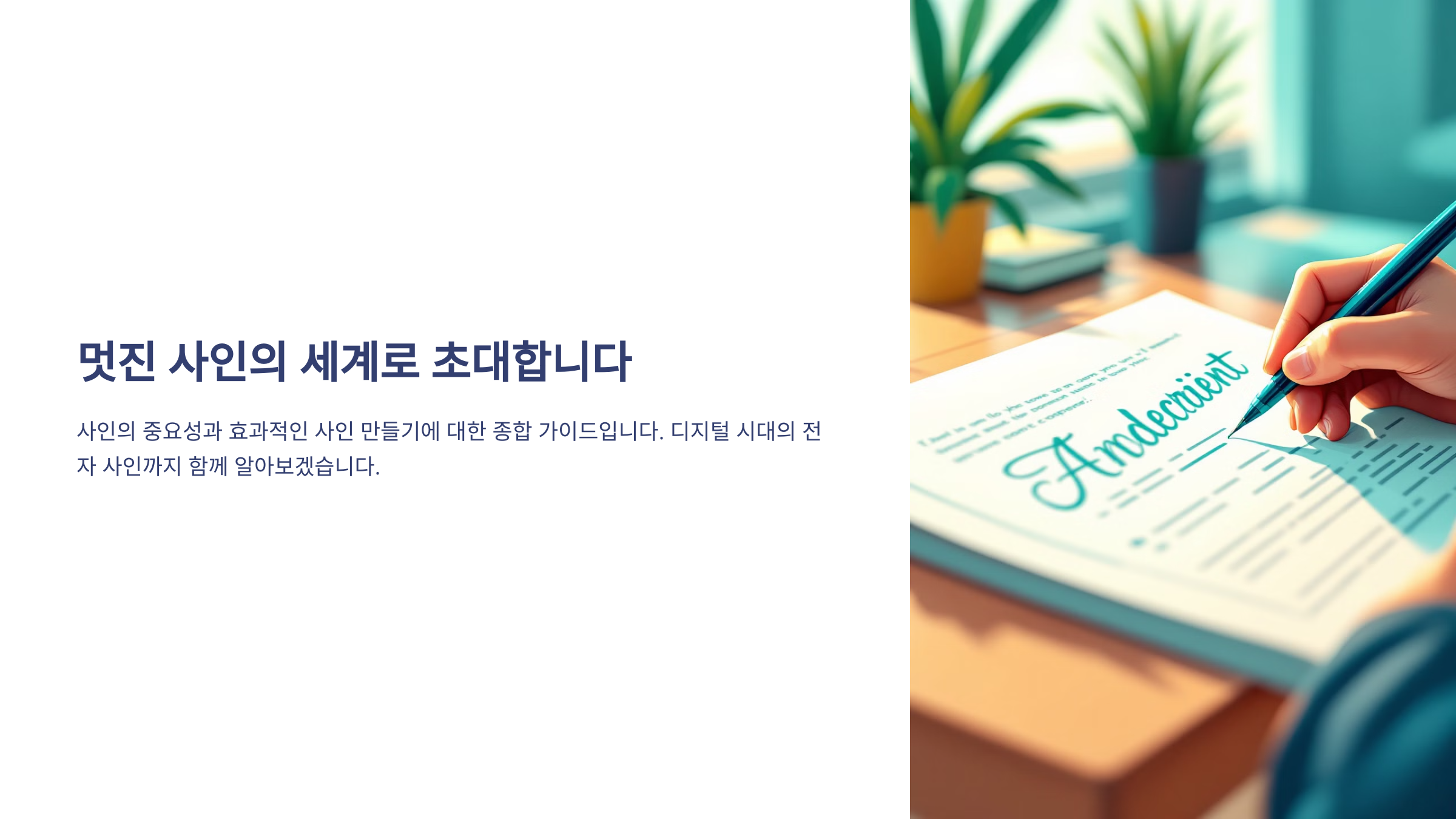
내가 생각했을 때, 멋진 사인은 단순하면서도 강렬한 인상을 주는 것이 중요해요. 한 글자만 바꿔도 느낌이 확 달라지기도 하고, 필기체를 응용하면 더욱 유니크한 디자인이 될 수도 있어요! 🎨
이제 본격적으로 멋진 사인을 만드는 방법에 대해 알아볼까요?
사인의 중요성 ✨
사인은 단순한 서명이 아니라, 자신을 표현하는 강력한 도구예요. 유명 연예인이나 스포츠 스타의 사인을 보면 한눈에 알아볼 수 있죠. 이것이 바로 사인이 가지는 브랜드 가치예요! 🌟
특히 예술가나 디자이너, 비즈니스맨에게 사인은 더욱 중요해요. 자신의 서명이 곧 하나의 트레이드마크가 되기도 하니까요. 예를 들어, 스티브 잡스나 일론 머스크 같은 유명 인물들은 사인 하나만으로도 강한 인상을 남기죠! 🚀
일상에서도 사인은 자주 쓰여요. 은행 서류, 계약서, 카드 서명까지, 우리가 사인을 하는 순간은 생각보다 많아요. 그렇다면 남들과 차별화된, 멋진 사인을 만들어야겠죠? ✍
📜 유명인의 개성 있는 사인 사례 🔍
유명인 사인의 특징 스티브 잡스 깔끔하면서도 독창적인 필기체 마이클 조던 강렬한 필체와 곡선 강조 일론 머스크 역동적이고 날렵한 스타일 방탄소년단(BTS) 각 멤버마다 개성 넘치는 디자인 이처럼 사인은 단순한 이름을 넘어서, 자신의 아이덴티티를 보여주는 중요한 요소예요. 그러면 어떻게 하면 나만의 멋진 사인을 만들 수 있을까요? 🎨
멋진 사인을 위한 기본 원칙 🎨
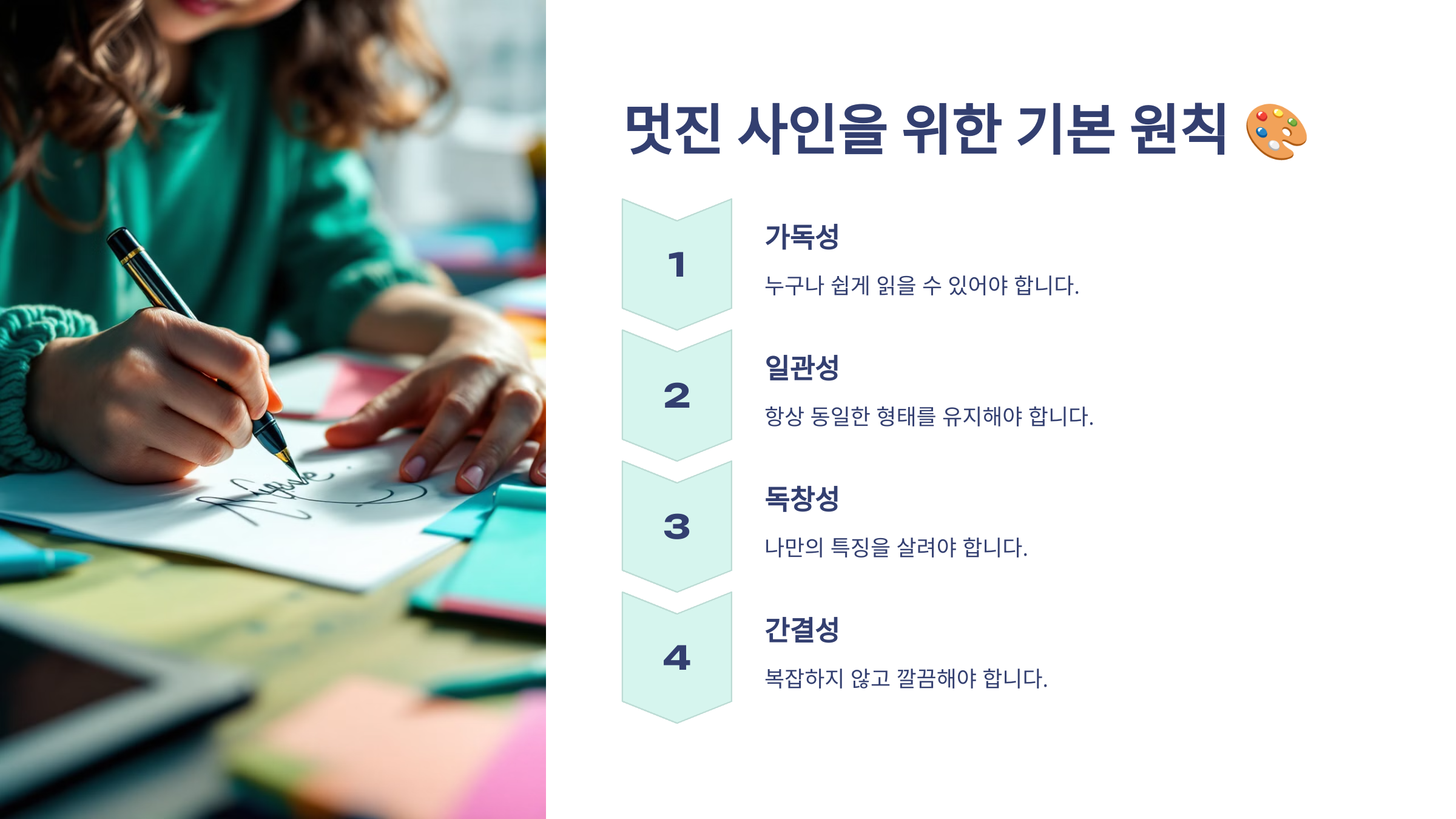
멋진 사인을 만들기 위해 몇 가지 기본 원칙을 알아야 해요. 사인은 단순할수록 기억에 남고, 직관적인 디자인이 중요하죠. 🖊
1⃣ 단순함이 최고! 복잡한 사인은 알아보기 어려워요. 최대한 간결하면서도 강렬한 인상을 주는 것이 중요해요.
2⃣ 개성을 담자! 필기체를 활용하거나, 자신만의 독특한 스타일을 만들어야 해요. 예를 들어, 자신의 이니셜을 강조하면 개성이 더욱 살아나요!
3⃣ 연습이 필수! 한 번에 완벽한 사인을 만들기는 어려워요. 다양한 스타일을 시도해 보고, 손에 익을 때까지 연습하는 것이 중요해요.
✏ 사인의 필수 요소 분석 🔬
요소 설명 필기체 자연스럽고 유려한 흐름을 만든다 이니셜 강조 첫 글자를 두껍게 쓰거나 크게 디자인 특별한 기호 별, 하트, 선 등의 장식 요소 추가 속도감 빠르고 날렵한 느낌을 살리기 이제 기본 원칙을 알았으니, 실전으로 들어가 볼까요? 한 글자만 바꿔도 사인의 느낌이 확 달라진다는 점, 알고 있었나요? 🔄
글자 하나만 바꿔도 느낌이 달라진다! 🔄
사인의 디자인에서 한 글자만 바꿔도 분위기가 확 달라질 수 있어요. 필기체를 다르게 쓰거나, 대소문자를 바꾸는 것만으로도 완전히 다른 스타일이 되죠. 🔠
예를 들어, ‘J.Kim’이라는 사인이 있다고 가정해봐요. ‘J’를 둥글게 쓰느냐, 직선으로 날카롭게 쓰느냐에 따라 느낌이 달라지고, ‘Kim’을 필기체로 연결하면 더 세련된 인상을 줄 수 있어요. ✍
이름을 풀네임으로 쓰는 대신, 이니셜만 활용하는 것도 좋은 방법이에요. ‘J.H.Kim’과 ‘JH Kim’만 비교해도 스타일이 확연히 달라 보이죠! 🙌
🔠 글자 스타일 변화에 따른 사인 차이 📌
스타일 특징 느낌 J. Kim 이니셜 강조, 심플한 디자인 깔끔하고 모던한 느낌 JH Kim 이니셜을 이어서 필기체로 작성 부드럽고 세련된 분위기 J. H. Kim 점(.)을 추가하여 정돈된 인상 고급스럽고 클래식한 느낌 JKim 이니셜을 연결하여 필기체 활용 자연스럽고 개성 있는 스타일 이처럼 작은 변화 하나만으로도 분위기가 달라지죠? 사인의 스타일을 결정할 때, 자신이 원하는 이미지에 맞게 글자 모양을 조정해 보세요! ✨
유명인들의 사인에서 배우는 포인트 🌟
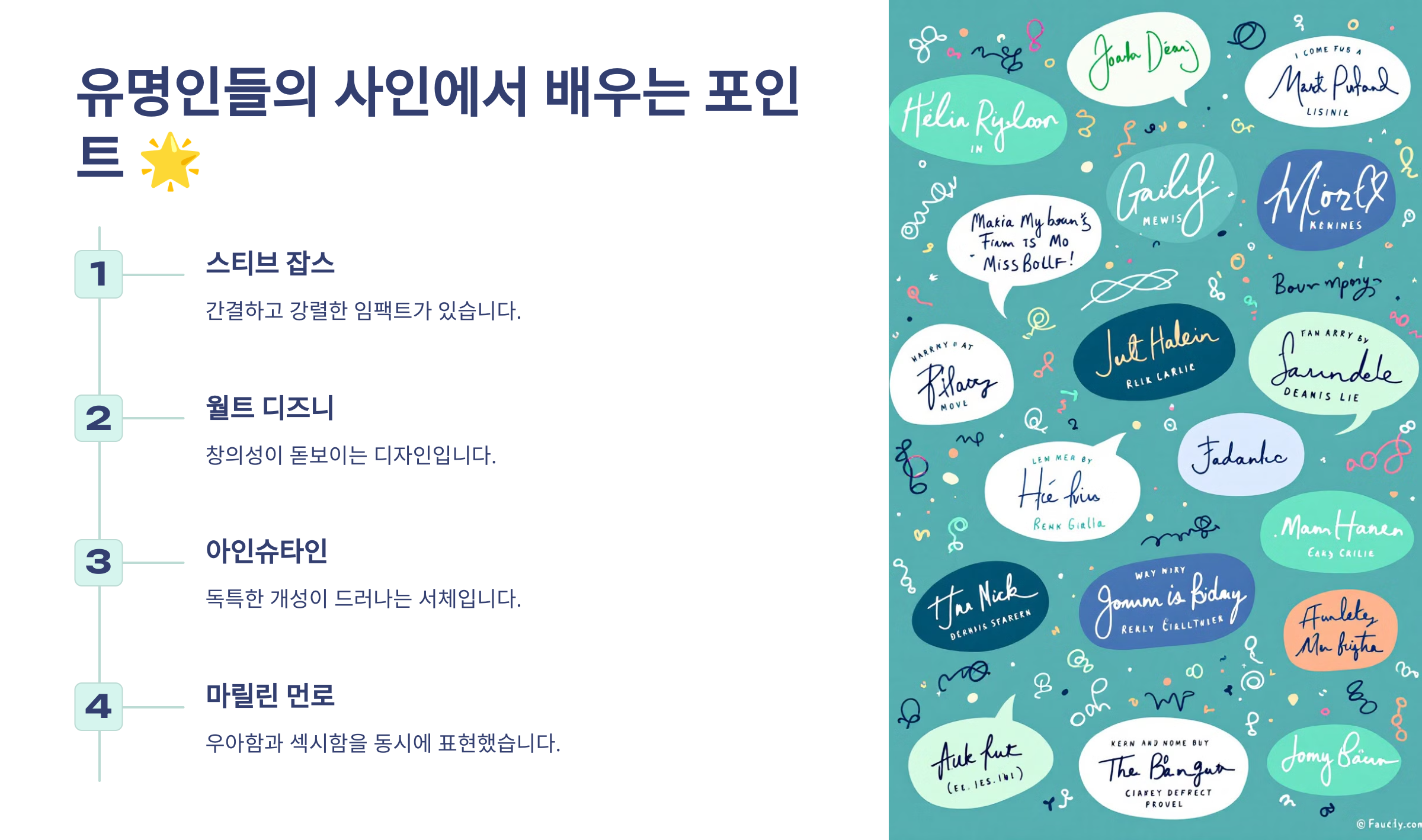
멋진 사인을 만들기 위해서는 이미 성공한 사람들의 사인을 참고하는 것도 좋은 방법이에요. 유명인들은 자신만의 개성을 살려 사인을 디자인하죠. 어떤 공통점이 있을까요? 🤔
🔹 필기체와 개성 있는 변형 많은 유명인들은 일반적인 글씨체를 그대로 쓰지 않고, 필기체를 변형하거나 이니셜을 독특하게 디자인해요.
🔹 강조되는 요소가 있다! 예를 들어, 마이클 잭슨의 사인은 ‘M’과 ‘J’를 강조하며, 일론 머스크는 날카로운 필체로 강렬한 인상을 줘요. 🚀
🔹 간결하면서도 알아볼 수 있는 디자인 너무 복잡하면 사인으로서의 기능이 떨어져요. 한 번 보고도 기억할 수 있는 스타일이 중요하답니다! ✍
🌍 유명인의 사인 스타일 분석 🔍
유명인 사인의 특징 느낌 스티브 잡스 깔끔한 필기체, 세련된 곡선 모던하고 혁신적인 느낌 일론 머스크 날카로운 필체, 속도감 있는 획 강렬하고 역동적인 인상 테일러 스위프트 부드러운 필기체, 곡선 강조 우아하고 예술적인 느낌 BTS 각 멤버마다 개성 넘치는 디자인 트렌디하고 유니크한 스타일 유명인의 사인을 보면, 단순하지만 강렬한 디자인이 많다는 걸 알 수 있어요. 이제 나만의 스타일을 적용해볼 차례예요! 🚀
멋진 사인을 쉽게 만드는 연습법 ✍
멋진 사인을 만들고 싶다면, 꾸준한 연습이 필요해요. 하지만 복잡하게 생각할 필요는 없어요! 몇 가지 간단한 방법으로 누구나 쉽게 멋진 사인을 만들 수 있답니다. 🚀
🔹 가장 편한 필기체를 찾아라! 자연스럽게 손이 가는 필기체를 먼저 찾아보세요. 억지로 따라 하기보다는 자신의 손에 익은 스타일이 중요해요.
🔹 이니셜을 활용하라! 풀네임을 쓰지 않아도 돼요. 이니셜만 강조하거나, 일부만 변형하는 것도 개성을 살릴 수 있는 좋은 방법이에요.
🔹 사인 속도 조절하기! 빠르게 사인을 하면 날렵한 느낌이 들고, 천천히 하면 정돈된 스타일이 돼요. 연습하면서 자신에게 맞는 속도를 찾아보세요. ⏳
📄 사인 연습을 위한 단계별 팁 🖊
단계 연습 방법 1단계 이름을 다양한 필기체로 써보기 2단계 이니셜을 강조한 스타일 시도하기 3단계 선 굵기와 크기 조절하면서 테스트 4단계 속도를 조절하며 스타일 정하기 5단계 자연스럽게 사인이 나올 때까지 반복 연습 연습을 꾸준히 하면 어느 순간 나만의 사인이 자연스럽게 만들어질 거예요! ✨ 이제 디지털 시대에 맞는 전자 사인도 함께 알아볼까요? 💻
디지털 시대, 전자 사인도 중요하다! 💻
이제는 종이에만 사인을 하는 시대가 아니에요. 온라인 계약, 전자 문서, 이메일 서명 등 디지털 환경에서도 사인의 역할이 커지고 있어요. ✍
🔹 전자 사인이란? 전자 서명 또는 디지털 사인은 종이 대신 전자 문서에 서명하는 방식이에요. PDF, 워드 파일, 이메일 등에 삽입할 수 있죠.
🔹 어디에 활용될까? 전자 사인은 계약서, 금융 거래, 공문서 등 다양한 곳에서 사용돼요. 빠르고 안전하게 서명할 수 있어 업무 효율이 높아져요! 🚀
🔹 전자 사인 만들기 마우스, 스타일러스 펜, 모바일 앱을 활용해 자신만의 전자 서명을 만들 수 있어요. PNG 형식으로 저장해 두면 여러 문서에 삽입하기 편리하답니다.
💾 인기 있는 전자 서명 도구 📌
도구 특징 DocuSign 전자 계약 및 법적 효력 지원 Adobe Sign PDF 문서에 직접 서명 가능 HelloSign Google Drive와 연동 가능 SignEasy 모바일에서 간편한 전자 서명 디지털 시대에는 종이 사인뿐만 아니라 전자 서명도 필수예요! 이제 FAQ를 통해 자주 묻는 질문을 정리해 볼까요? ❓
FAQ ❓
Q1. 멋진 사인을 만들 때 가장 중요한 요소는 무엇인가요?
A1. 가장 중요한 요소는 간결함과 개성이에요. 사인은 너무 복잡하면 알아보기 어렵고, 너무 단순하면 개성이 부족할 수 있어요. 자신의 스타일을 살리면서도 자연스러운 흐름을 가지는 것이 중요해요. ✍
Q2. 필기체를 잘 못 써도 멋진 사인을 만들 수 있나요?
A2. 물론이죠! 필기체가 아니어도 독창적인 디자인을 적용하면 멋진 사인을 만들 수 있어요. 이니셜을 강조하거나, 간단한 기호를 추가하는 것도 좋은 방법이에요. 😊
Q3. 한 글자만 바꿔도 사인의 느낌이 달라진다고요?
A3. 맞아요! 예를 들어 'J.Kim'과 'JH Kim'의 차이만 봐도 스타일이 달라지죠. 이니셜 활용법이나 글자의 연결 방식을 조정하면 완전히 다른 느낌을 줄 수 있어요. 🔄
Q4. 전자 서명도 법적 효력이 있나요?
A4. 네! 전자 서명은 법적으로 인정되는 경우가 많아요. 특히 DocuSign이나 Adobe Sign 같은 공인 전자 서명 도구를 사용하면 법적 효력을 갖출 수 있어요. 📜
Q5. 연예인들은 어떻게 사인을 디자인할까요?
A5. 연예인들은 보통 이니셜을 변형하거나, 필기체를 독특하게 조합해요. 때로는 작은 아이콘(별⭐, 하트❤ 등)을 추가해 개성을 살리기도 해요!
Q6. 사인 연습을 효과적으로 하는 방법이 있나요?
A6. 효과적인 방법은 반복 연습이에요! 먼저 여러 스타일을 시도해보고, 손에 익을 때까지 연습해 보세요. 선 굵기와 속도 조절도 중요한 포인트예요. 🎨
Q7. 디지털 기기에서 사인을 쉽게 만들 수 있는 방법이 있나요?
A7. 네! 태블릿과 스타일러스 펜을 사용하면 쉽게 만들 수 있어요. 모바일 앱(예: Adobe Sign, HelloSign)에서도 전자 사인을 제작할 수 있답니다. 💻
Q8. 멋진 사인을 만들기 위한 최종 팁이 있나요?
A8. 자연스럽고 개성 있는 스타일을 찾는 것이 핵심이에요. 사인의 흐름이 부드러워야 하고, 자신만의 독창적인 요소를 추가하면 더 멋진 사인이 완성돼요! 🚀
지금까지 멋진 사인을 만드는 방법을 알아봤어요! 이제 직접 연습해보면서 나만의 멋진 사인을 완성해 보세요. ✨